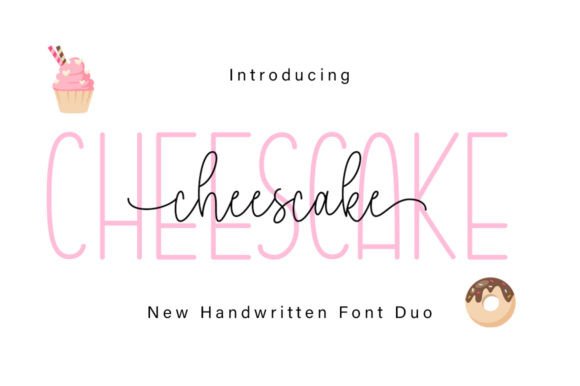
Cheescake Duo
Jika anda sedang mencari aset berkualiti tinggi seperti Cheescake Duo, pakej premium ini merupakan pilihan yang hebat untuk projek kreatif anda.
Sama ada anda mencipta produk POD (Print on Demand), jemputan perkahwinan atau grafik media sosial, Cheescake Duo amat bersesuaian.